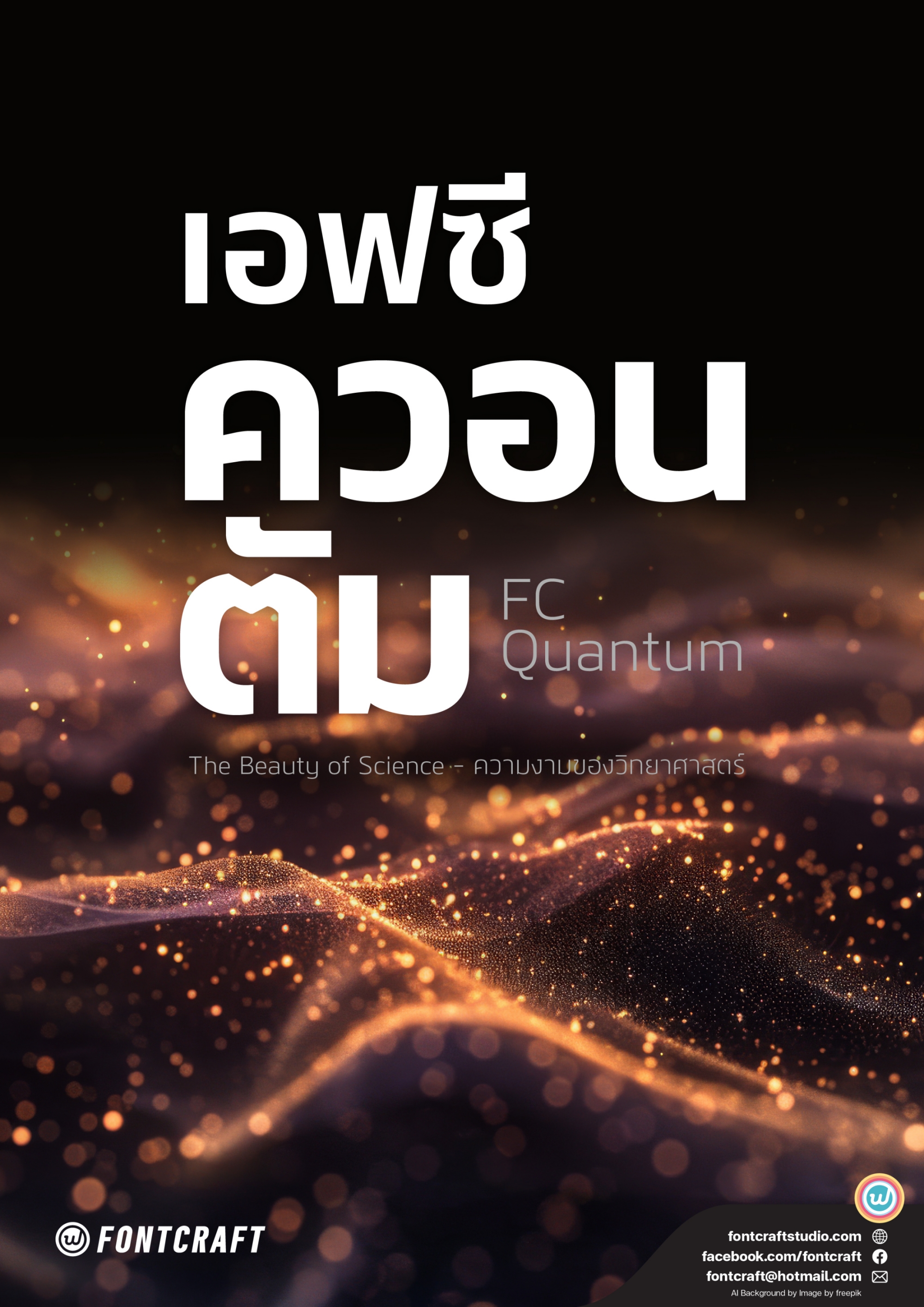
เอฟซี ควอนตัม (FC Quantum)
The Beauty of Science ความงามของวิทยาศาสตร์
ฟอนต์เอฟซี ควอนตัม (FC Quantum)
The Beauty of Science ความงามของวิทยาศาสตร์
จากโจทย์ที่ต้องการสร้างแบบอักษรไร้หัวที่มีโครงสร้างดูภูมิฐานและภาพลักษณ์ที่ทันสมัย เหมาะสำหรับการใช้เพื่อเสริมภาพลักษณ์ด้านวิทยาศาสตร์และเทคโนโลยี พร้อมก้าวไปสู่อนาคต มีให้เลือกใช้ครอบคลุมในทุกระดับน้ำหนัก และปรับได้โดยละเอียดผ่าน Variable Font